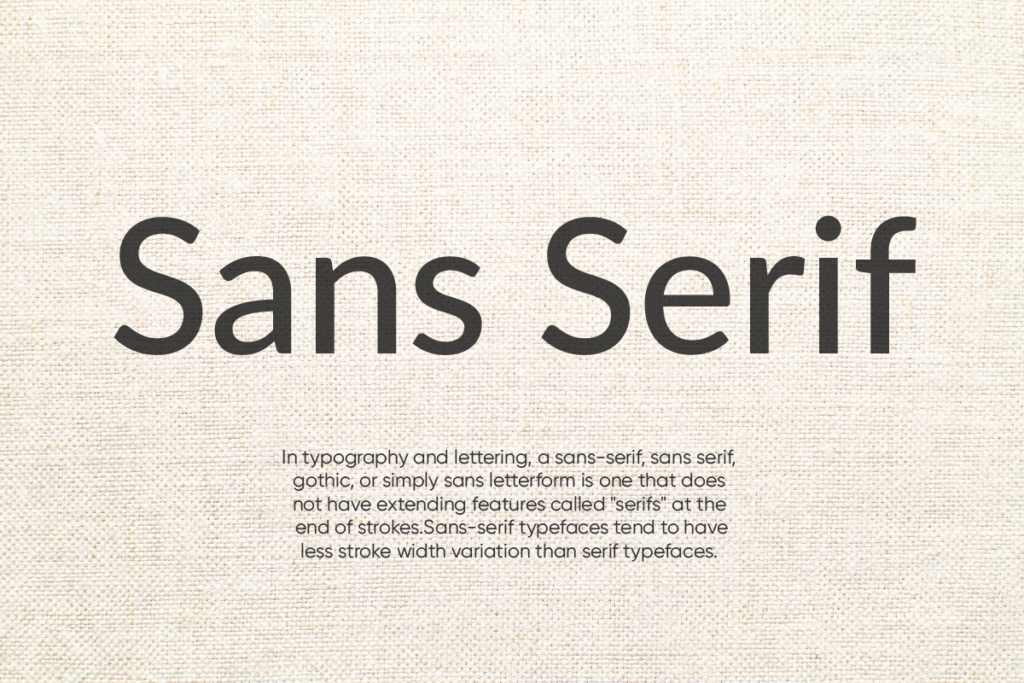
Font Sans Serif là sự lựa chọn tuyệt vời cho những thiết kế đòi hỏi sự hiện đại, rõ ràng và dễ đọc. Font Sans Serift là một font chữ thuộc bộ font chữ không chân. Được đặc trưng bởi các đường nét sạch sẽ và không có chân chữ, phông chữ Sans Serif mang đến một phong cách tối giản, phù hợp cho nhiều loại dự án từ thiết kế web, logo, đến các ấn phẩm in ấn. Với khả năng dễ dàng kết hợp với các phong cách khác, Font Sans Serif không chỉ giúp truyền tải thông điệp một cách trực tiếp và hiệu quả, mà còn tạo nên vẻ đẹp thanh lịch và chuyên nghiệp cho bất kỳ thiết kế nào.